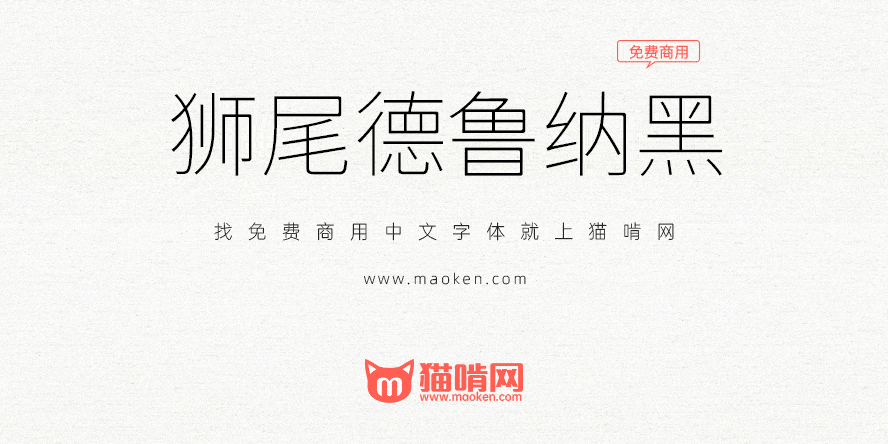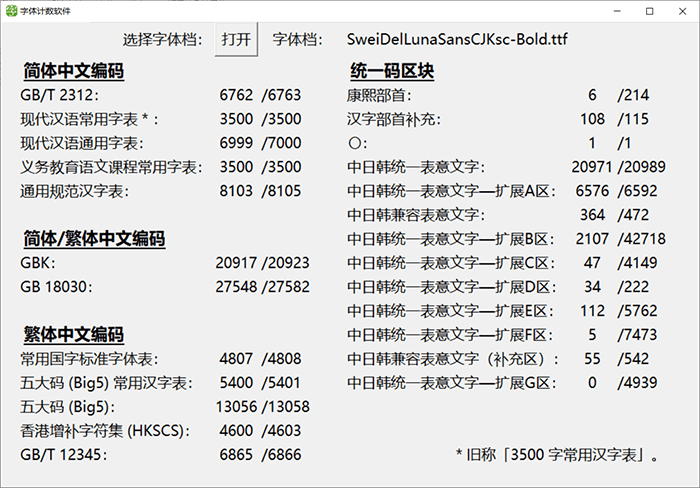
字体作者:Max(中国台湾) | 字体字重:7个 |
狮尾德鲁纳黑体基于思源黑体的右侧变圆和拔脚改造,更加简明现代化的字体。支援简体中文、繁体中文、韩文与日文;可以免费商用,欢迎大家自由应用、自由优化、自由改作!
狮尾德鲁纳黑体与狮尾D露西差别在笔触是否有做调整,狮尾德鲁纳黑体所套用的效果较少,在笔触没有做调整。